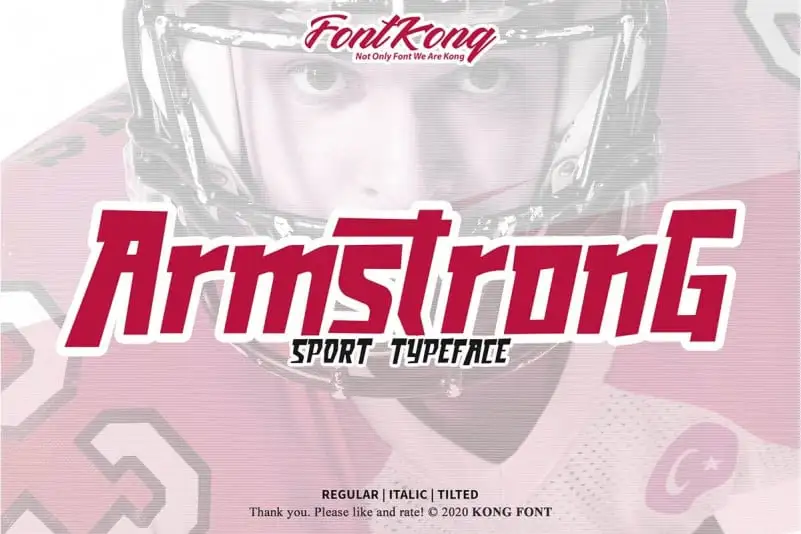
Armstrong Display Font – Download Grátis
A Armstrong Display Font oferece uma visão divertida e desafiada das linhas de papel cortadas. Desenhada e compartilhada por fontkong, esta font é perfeita para criar invitações adoráveis para casamentos, aniversários ou dias especiais. A coleção de letras e números também é ideal para sua próxima projeto, seja uma logomarca, design de marca, ilustração digital, design do tênis/camiseta, banner, revista, sinalização ou campanha publicitária. Ela se adapta perfeitamente a várias necessidades criativas e pode ser usada em um vasto range de projetos. É uma fonte visualmente atrativa que certamente encantará seus projetos mais elaborados.